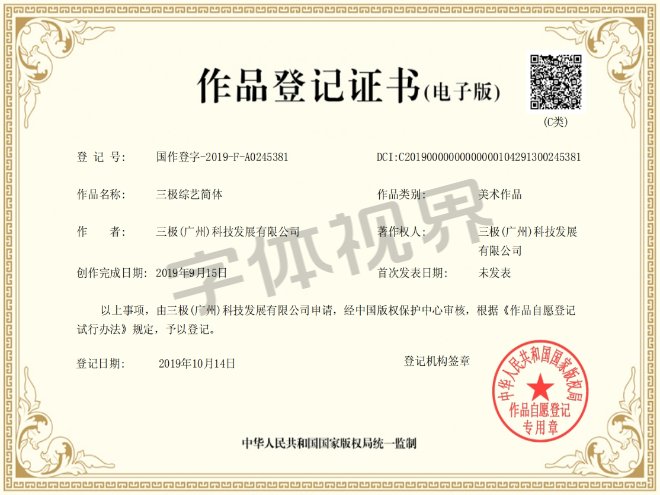
三极综艺简体-80发布
字体名称:三极综艺简体-80
字体类别: 创意字体
适用场景:屏幕显示、影视、动漫
三极综艺简体-80简介:三极综艺简体是一款家族字体,其结构严谨,字型修饰得宜,恰到好处,整体规范而不失特色。严谨秀气而从容和优雅,让人赏心悦目,百看不厌。可广泛用于书刊、广告、包装、店招、影视以及社交网络个性化用字。